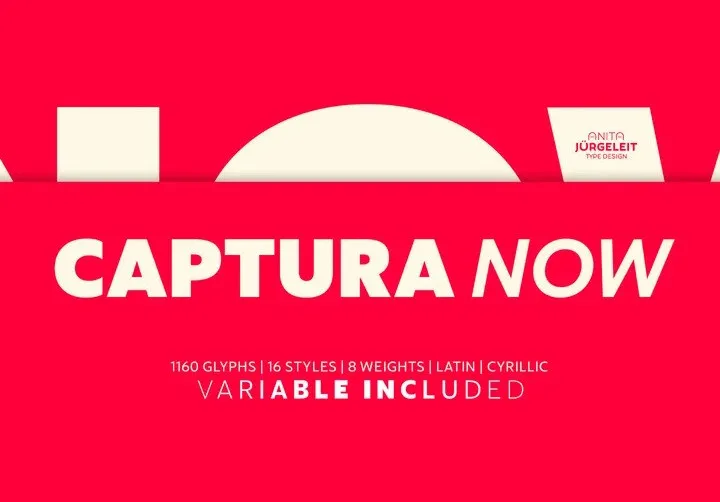
Captura Now é uma família de tipografia geométrica que se destaca por sua combinação casual e formal. Esta fonte é composta de 18 variante e oferece um design suave e equilibrado, criando o ritmo perfeito para a fonte Captura Now. Suas formas meticulosamente refinadas e espaçamento cuidadosamente ponderado resultam num aspecto acolhedor que confere uma face amigável à fonte. Com uma extensa coleção de caracteres, Captura Now oferece liberdade para transformar sua criação em o mundo da escrita cílindrica, bem como em qualquer linguagem baseada no latim – incluindo vietnamita. Esta fonte é perfeita tanto na forma quanto no contorno, tornando-a uma opção ideal para designers que buscam um equilíbrio entre formas geométricas e design elegante.